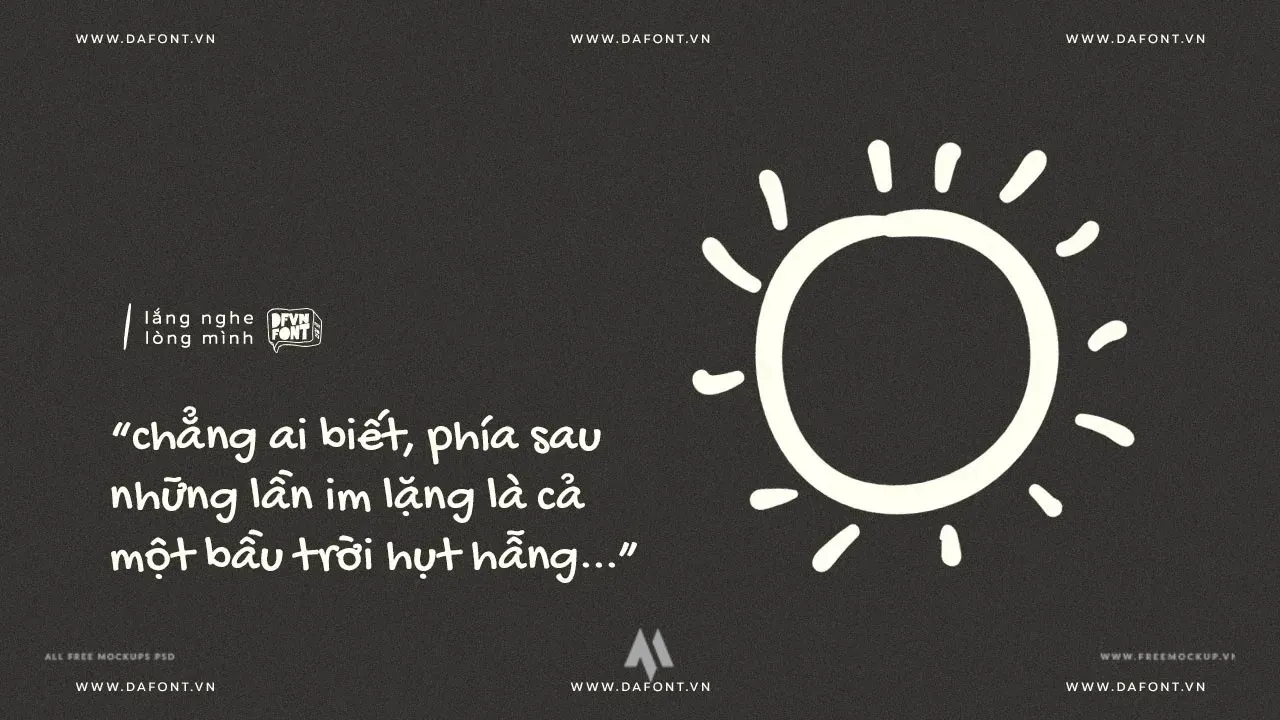
Download font DFVN Gochi Hand Việt hóa miễn phí (Huerta Tipográfica). Font chữ viết tay tự nhiên, tươi mới, hỗ trợ gõ tiếng Việt chuẩn cho thiết kế và Canva.
Gochi Hand là một trong những font chữ viết tay (Handwriting font) nổi bật và được yêu thích hàng đầu trên thư viện Google Fonts, được sáng tạo bởi studio danh tiếng Huerta Tipográfica.
- Nét chữ tự nhiên, phóng khoáng: Mô phỏng chân thực nét bút viết tay nhẹ nhàng, không gò bó, mang lại cảm giác thân thiện và gần gũi.
- Đơn giản nhưng tinh tế: Dù mang phong cách tự do, các ký tự của Gochi Hand vẫn duy trì cấu trúc rõ ràng, đảm bảo độ đọc (readability) tốt ngay cả ở kích thước nhỏ.
- Phong cách trẻ trung, hiện đại: Giúp thổi một làn gió tươi mới vào các thông điệp truyền thông.